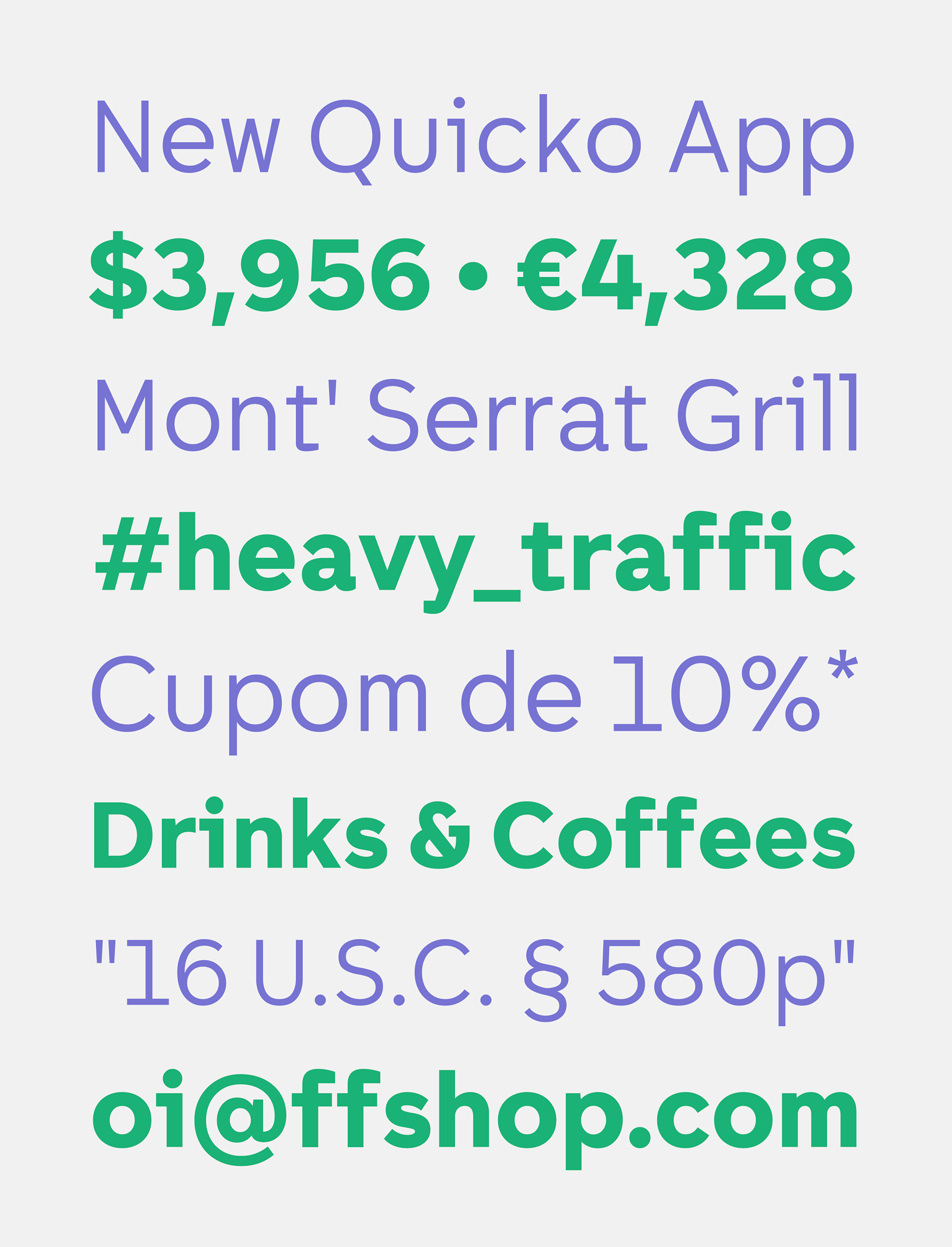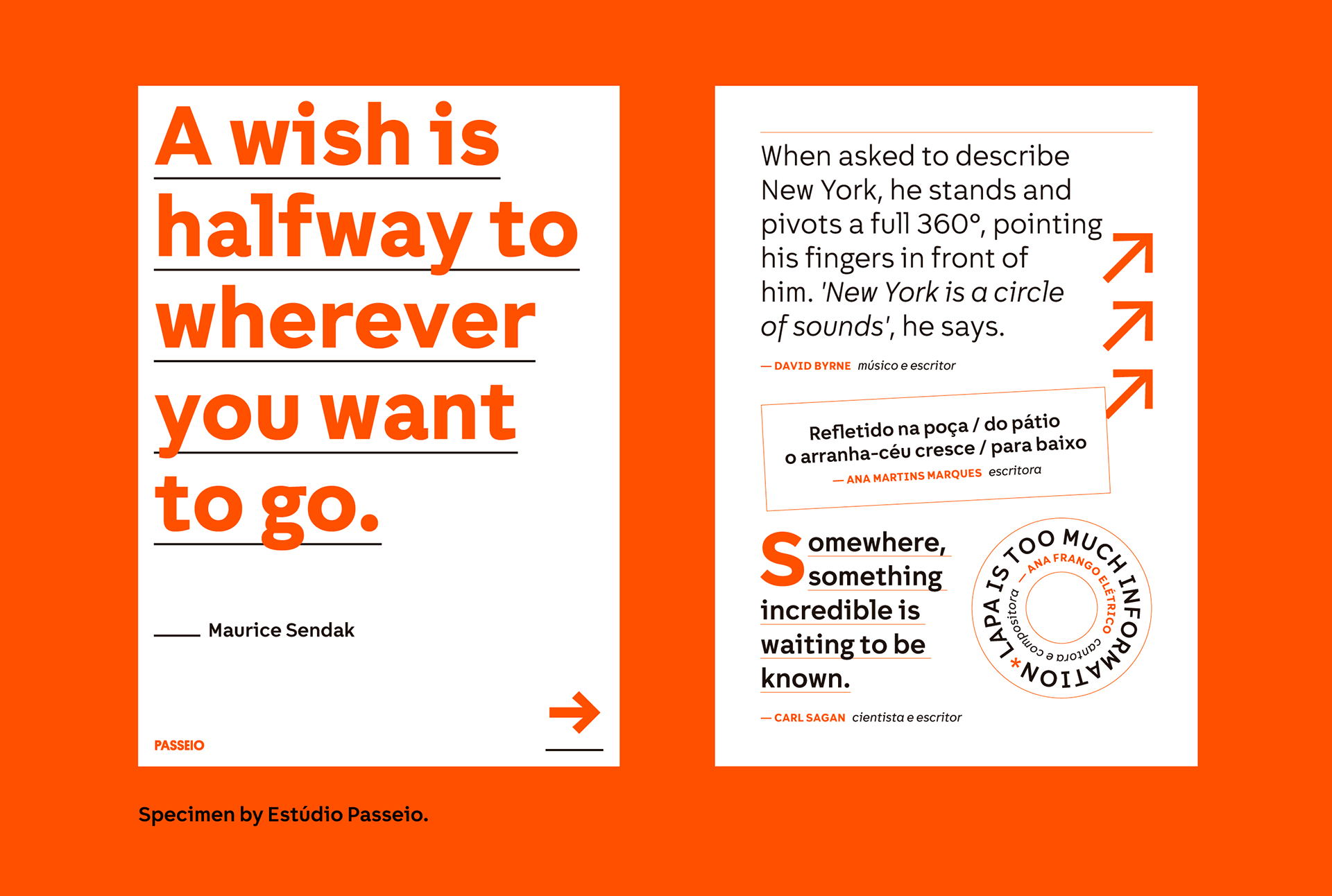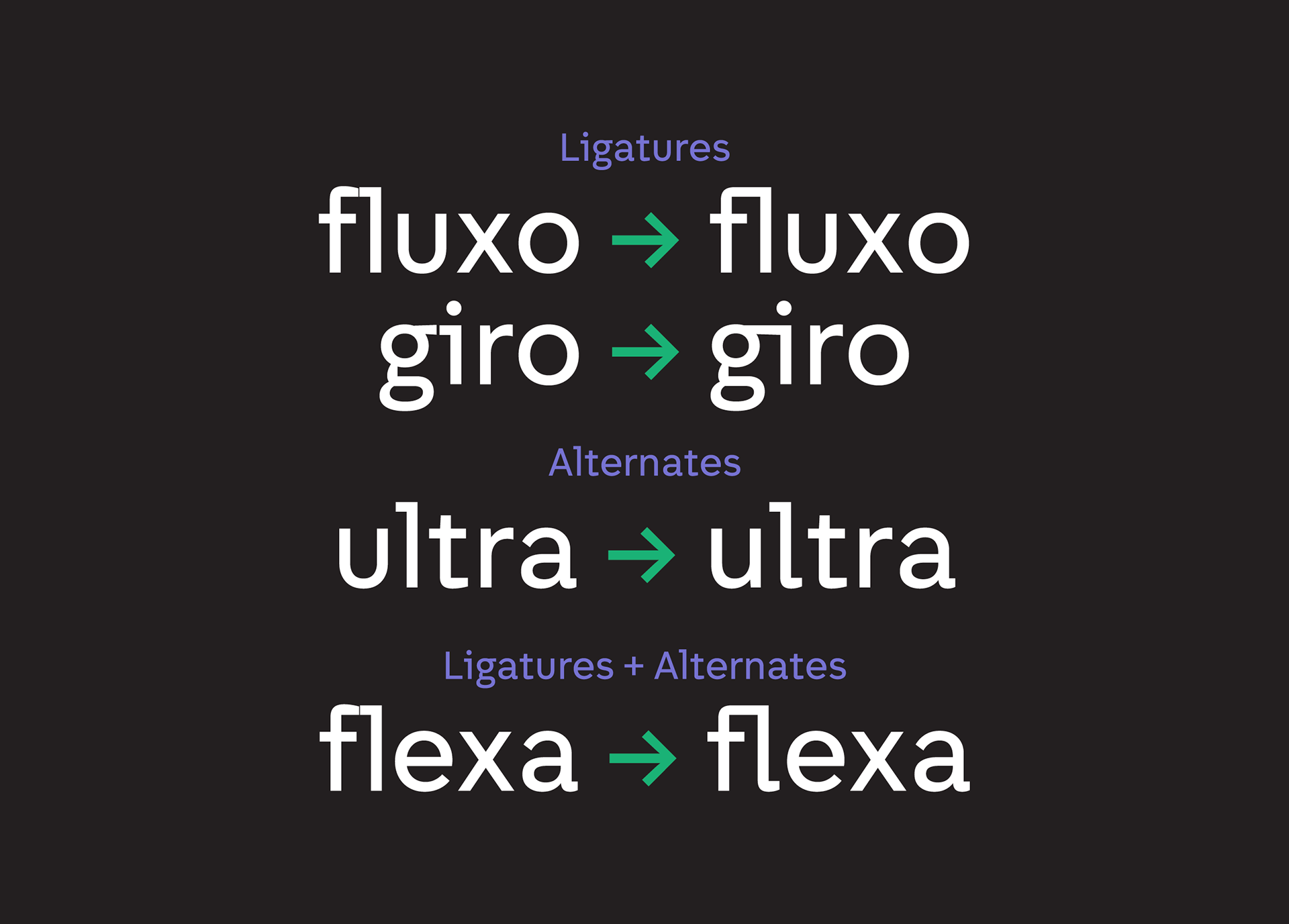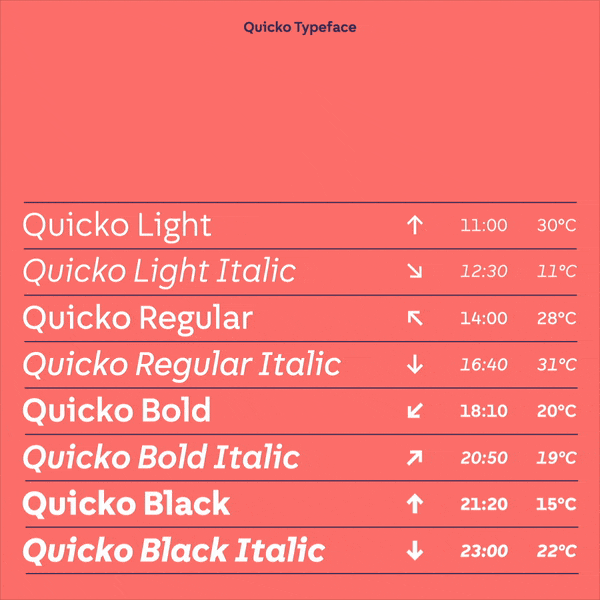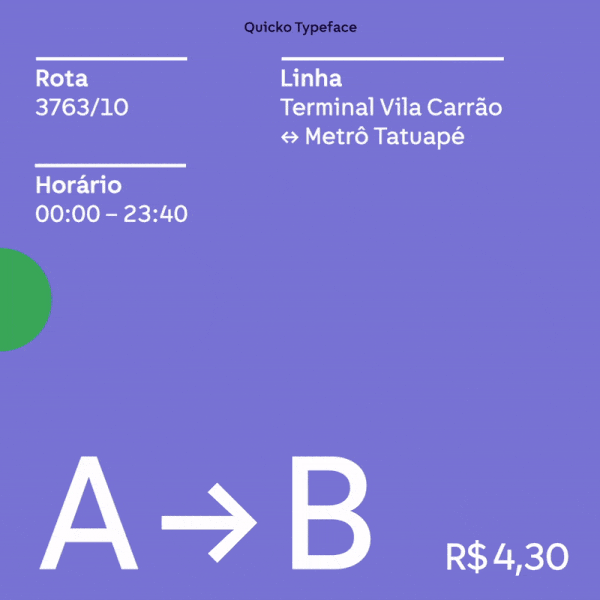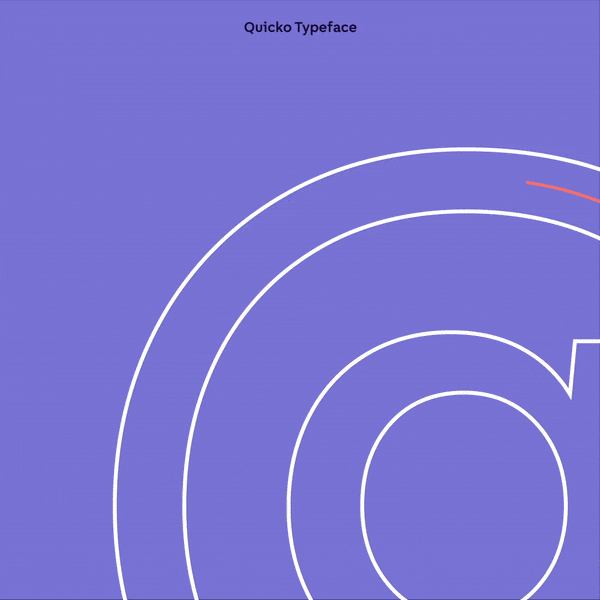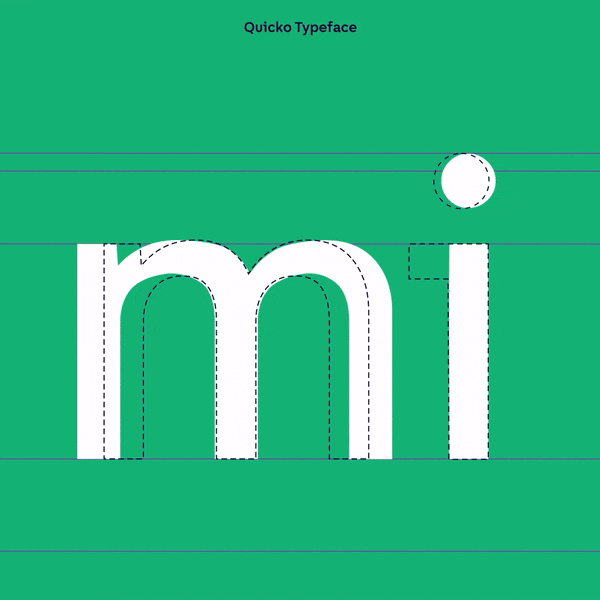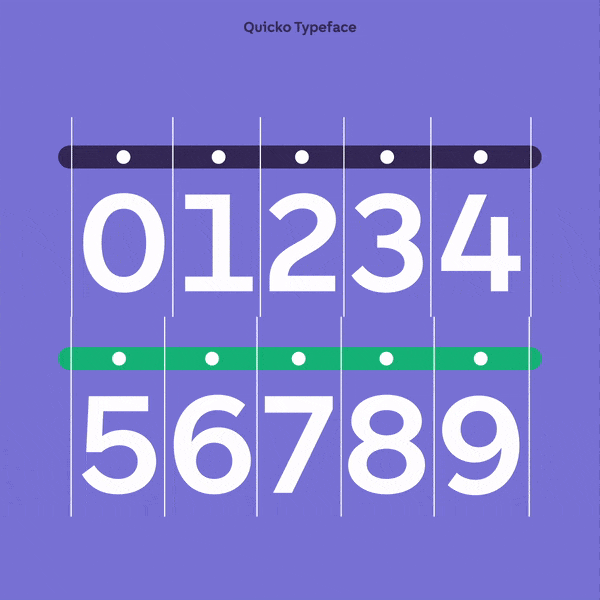
Quicko é um agregador de conveniências digital. A partir da consulta por uma localização, o assistente da Quicko combina trajetos e rotas de diferentes meios de transporte e apresenta a opção mais conveniente de valor e tempo de viagem. Junto com o Estúdio Passeio, desenhamos uma tipografia exclusiva para a Quicko.
Quicko is a digital convenience aggregator. By setting a destination location, the Quicko`s assistant combines routes from different modes of transport and presents the most convenient choice of value and travel time. In partnership with Estúdio Passeio, I designed an exclusive typography for Quicko.
Uma das características mais fortes do desenho da Quicko vem da sua inspiração nas fontes mono espacejadas, presentes tanto em máquinas de escrever quanto nos códigos por trás dos produtos digitais mais inovadores. Letras estreitas como o ‘I’ ganham serifas e outras mais largas como o M passam a ocupar menos espaço horizontal. Essas decisões, além de contribuírem para uma aparência dinâmica e descontraída, inserem a família no universo tipográfico das empresas de tecnologia.
One of the strongest features of Quicko's design comes from its inspiration in the mono-spaced fonts, present in both typewriters machines and codes behind the most innovative digital products. Narrow letters like ‘I’ gain serifs, and wider letters like M take up less horizontal space. These decisions, in addition to contributing to a dynamic and relaxed appearance, insert the family into the typographic universe of technology companies.